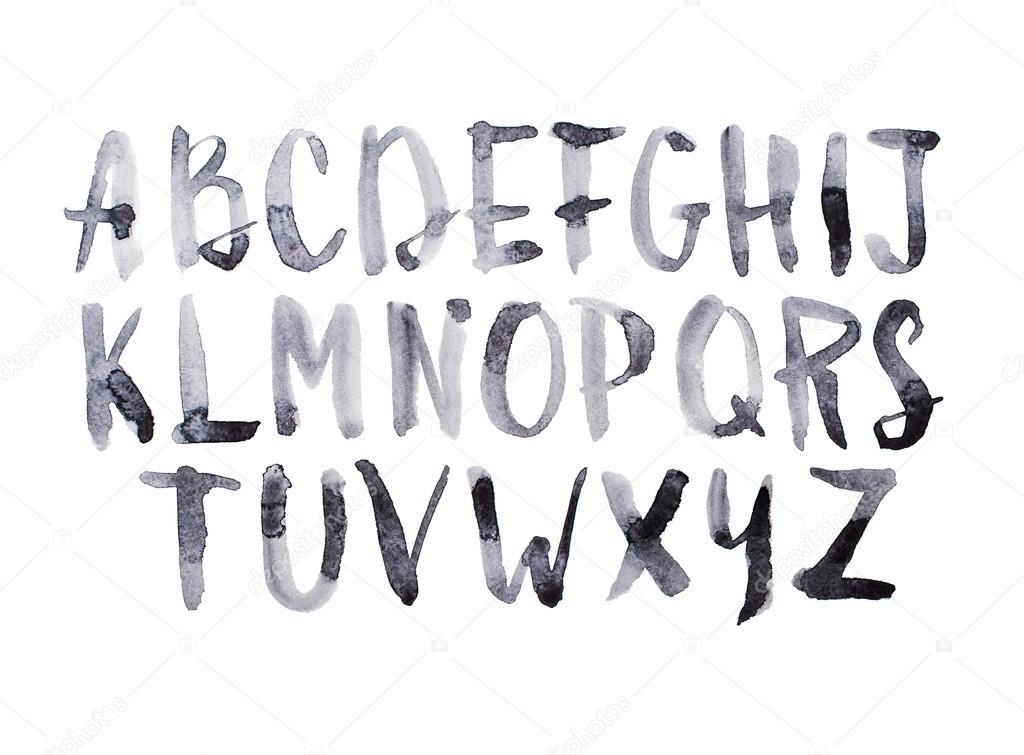
Общие характеристики шрифтов
Существует сложившаяся терминология, позволяющая охарактеризовать каждый конкретный шрифт по всем его параметрам.
Гарнитура шрифта (Type family) — совокупность шрифтов, объединенных общими стилевыми признаками, отличными от других шрифтов, т.е. совокупность начертаний, объединенных общим характером графического построения знаков и решением их элементов. Некоторые гарнитуры располагают большим количеством начертаний, чем другие. Благодаря этому можно построить весь документ на одной гарнитуре, используя где это необходимо различные варианты начертаний.
Примером может служить шрифт Helios который насчитывает около 33 начертаний.
Начертание (Type face) — комплект строчных и прописных знаков, цифр, знаков препинания, спецзнаков и символов. Начертания шрифтов любой гарнитуры отличаются цветовой насыщенностью, пропорциями, контрастностью и наклоном знаков (светлое, полужирное, курсивное или наклонное, нормальное, узкое или широкое).
Насыщенность шрифта определяется изменением толщины основных и соединительных штрихов одноименных знаков в различных начертаниях. В рамке одной гарнитуры насыщенность может изменяться от сверхсветлой до сверхжирной (light — ultra bold). Непрерывный ряд начертаний составляют: светлое (light), нормальное (regular, book), полужирное (demi), жирное (bold), темное (heavy), черное (black) и сверхжирное (extra bold).
Пропорции шрифта — показатель изменения ширины одноименных знаков в начертаниях одной гарнитуры от сверхузких до сверхшироких.
Контрастность — один из основных признаков шрифта, выраженный отношением толщины соединительных штрихов к толщине основных штрихов знаков. Эта характеристика изменяется от неконтрастных до сверхконтрастных шрифтов.
Кегель (size) — величина шрифта в наборе, определяется в пунктах. Кегль — это величина площадки, на которой размещается знак. Размер, шрифта определяется его высотой, измеренной в типографских пунктах (point или pt): 12 пунктов = 1пике, 6 пик одному дюйму.
Комплектность (полиграфический алфавит) — совокупность всех знаков, необходимых для набора текста: строчных, прописных, цифр, знаков препинания, спецзнаков и символов.
Наклон — наклон знака определяется углом, который он образует с вертикальной осью.
Интерлиньяж — расстояние между базовыми линиями соседних строк. Оно измеряется в пунктах и складывается из кегля шрифта и расстояния между строками.
Например, кегль 10 пунктов при расстоянии между строками в 2 пункта называют кеглем 10 пунктов при интерлиньяже 12 пунктов.
Выключка — параметр показывающий размещение текста в параграфе. Выключка бывает: по левому краю, по правому краю, по центру, по формату и полная выключка. В зависимости от выбранного типа выключки текст размещается по разному, текст этой статьи набран с выключкой по левому краю.
Существует еще такое понятие как удобочитаемость шрифта, но оно скорее носит субъективный характер и зависит не только от характеристик самого шрифта, но и от условий его применения.
Типы шрифтов
Все шрифты можно классифицировать на три основных группы — шрифты с засечками (антиква), без засечек (гротески или рубленные) и шрифты свободного стиля.
Шрифты с засечками (serif)
Это поперечные элементы на концах штрихов буквы. Шрифты с засечками также называют антиквенными, то есть античными, древними. Дело в том, что впервые подобные элементы у букв применили еще римляне.
Шрифты без засечек (sans-serif)
В шрифтах без засечек отсутствуют завершающие элементы на концах штрихов. Название sans-serif происходит от французского sans — без.
Рукописные шрифты (script)
Напоминают ручное письмо. Традиционно к ним относятся каллиграфические шрифты.
Декоративные шрифты
Эту категорию составляют многочисленные шрифты, которые не укладываются в обычные группы. Чаще всего их используют в заголовках и выделениях, чтобы подчеркнуть новизну, яркость, индивидуальность.
Альтернативные шрифты
В данную группу входят шрифты которые созданы в собственном ни на что не похожем стиле. В основном это новые виды шрифтовых форм, созданные производителями совсем недавно, и не несущие в основе другие шрифты. Их применение пока рассматривается в основном в качестве броских заголовков (примерно там же где и декоративные шрифты).
Книга Виллу Тоотса «Современный шрифт». Год издания 1960
Rosco — эффектный шрифт с кистью, который можно скачать и использовать бесплатно. Взгляните и используйте его для ваших текущих и будущих проектов. Он имеет очень личную атмосферу и придаст индивидуальности вашим проектам типографики и графического дизайна.
Здесь у вас есть прекрасный шрифт кисти, который вы можете использовать для своих текущих и будущих проектов. Этот шрифт имеет рисованный дизайн с естественными линиями. Он был создан Марсело Рейсом Мело, и он отлично смотрится в любом проекте, придавая индивидуальный подход к вашим текстам и дизайнам.